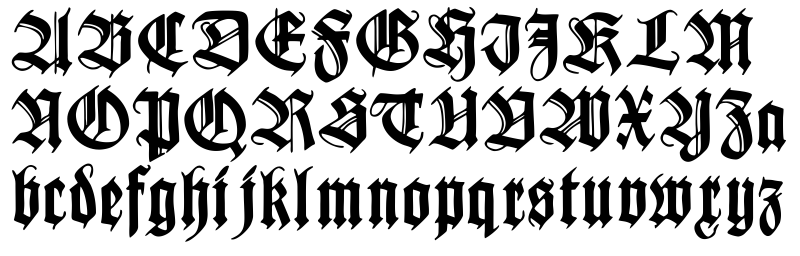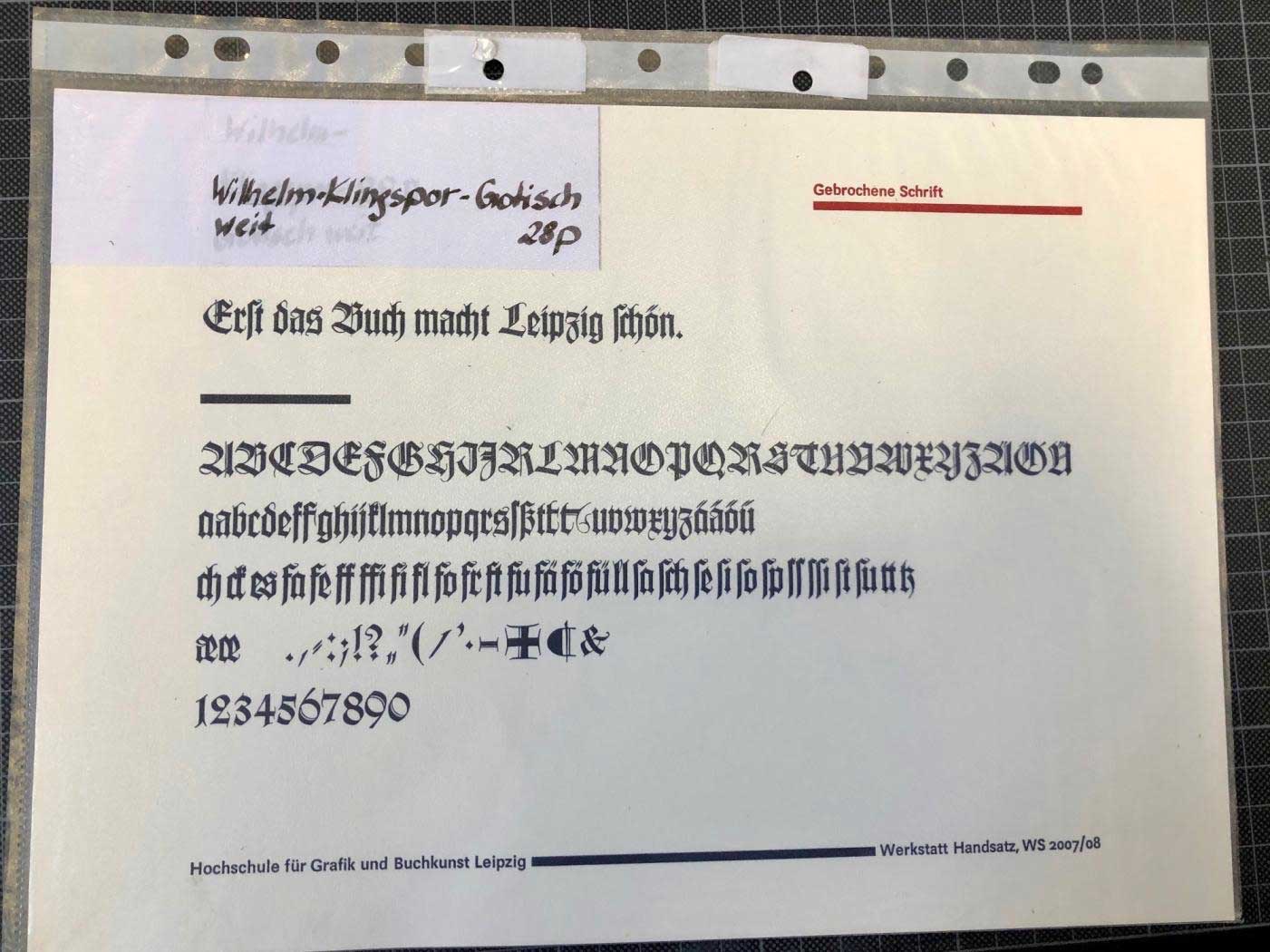
Mir fehlt ein Name dazu
Ich habe vor längerer Zeit eine Abbildung einer Schrift gefunden, die ich nachgezeichnet habe, die ich jetzt in mein Sortiment aufnehmen möchte. Mir fehlt aberr ein geeigneter Name dazu. Hilfe!
Hallo, ihr Lieben, mein Name ist Iris Köhler. Seit 49 Jahren übe ich meinen Beruf als Schriftsetzerin aus (Lehre und Arbeit im Grafischen Großbetrieb INTERDRUCK; seit Ende August 1981 arbeite ich in der Werkstatt Handsatz in der Hochschule für Grafik und Buchkunst Leipzig) ... und ich weiß, wie diese Schrift heißt. Es ist die "Wilhelm-Klingspor-Gotisch weit". Als wir vor Jahren diese Schrift bekommen haben, stand an dem Kasten "Klingspor". Eine längere Recherche zu verschiedenen Schriften brachte mich auf den richtigen Namen. Der Gestalter der Schrift ist Rudolf Koch.
Sorry, es heißt nur "Wilhelm-Klingspor-Gotisch" (ohne das "weit"). Da ist mir ein Fehler unterlaufen. Ich bitte um Verzeihung. Gruß Iris